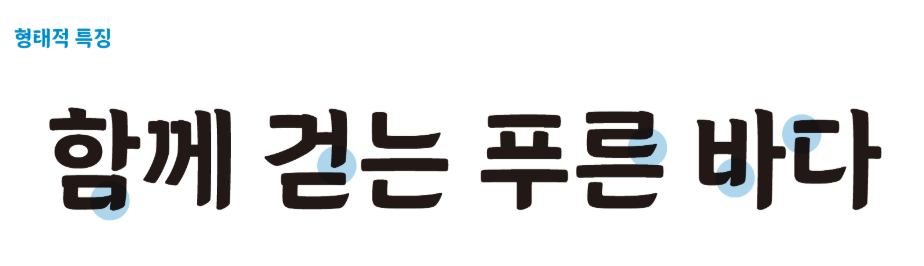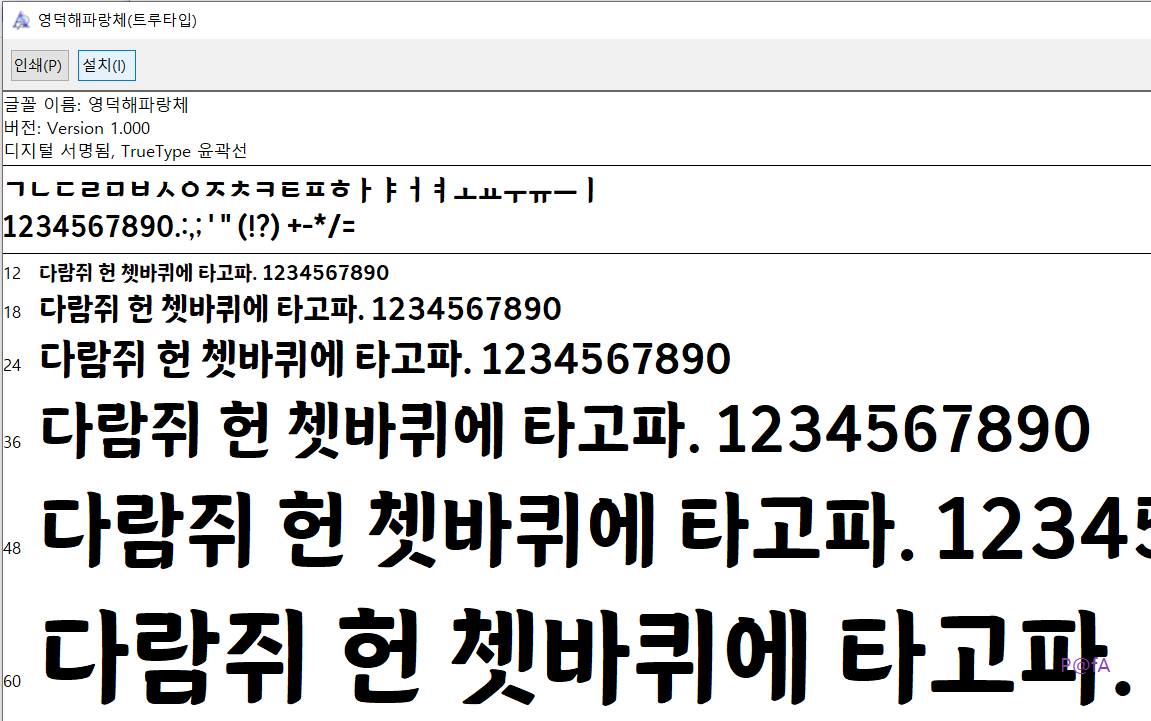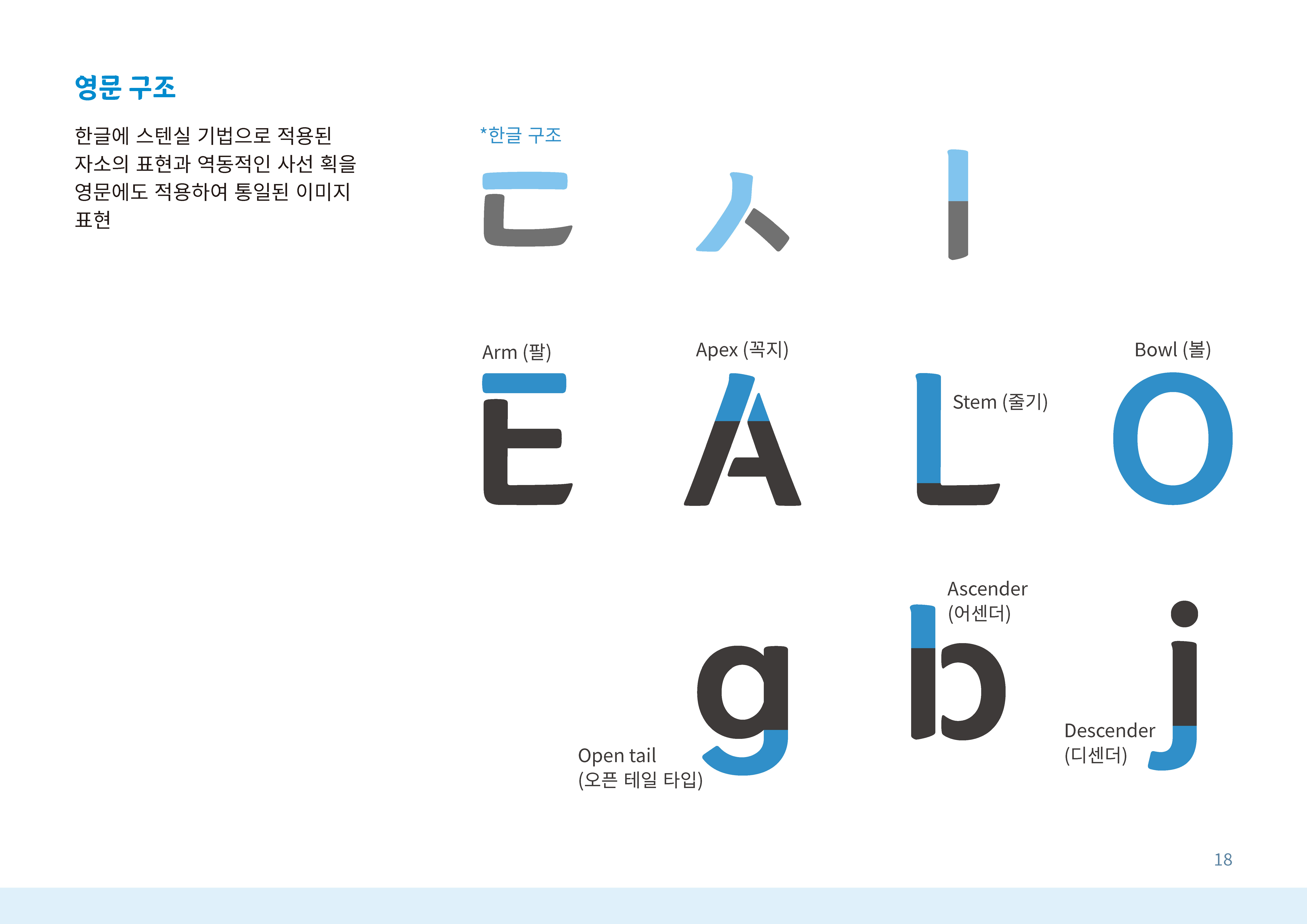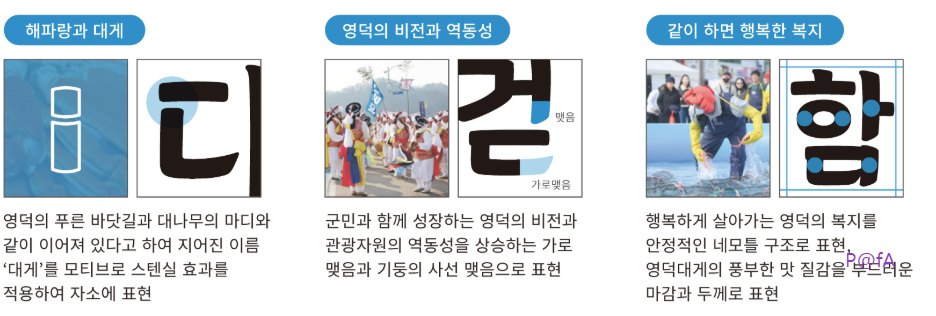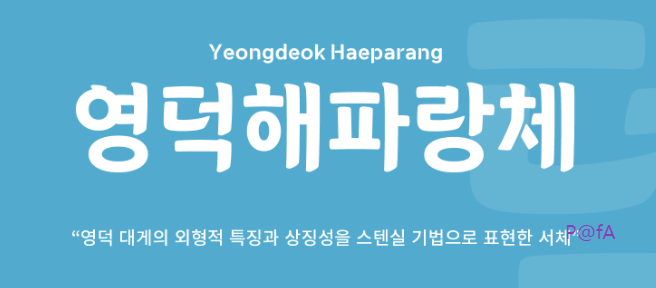
일부 자소에서 끊어진 듯 이어지는 효과가 나타나는 스텐실 폰트인 영덕 해파랑체를 다운로드하는 방법을 살펴본다. 더불어 누구나 무료로 사용 가능한 영덕 해파랑체를 컴퓨터에 설치하는 방법과 코딩 시에 활용하는 방법도 살펴본다.
스텐실 폰트 영덕 해파랑체 무료 다운로드
개인 및 기업 사용자에게 무료로 제공되는 즉, 누구나 개인적인 용도뿐만 아니라 상업적인 용도 즉, 영리 또는 비영리 목적으로도 무료로 사용할 수 있도록 제공하는 무료 폰트인 영덕 해파랑체를 소개한다. 영덕군은 자체 문서 및 책자, 안내판, 도시경관 등 실생활에 두루 사용할 수 있도록 무료로 제공하고 있다. 다음에서 영덕을 대표하는 대게의 외형적 특징과 상징성을 스텐실 기법으로 표현한 영덕 해파랑체를 무료로 다운로드해서 컴퓨터에 설치하는 방법을 비롯해서 사용하는 자세한 방법을 확인할 수 있다.
위의 이미지에서 보듯이 영덕 해파랑체는 일부 자소에 끊어진 듯 이어지는 스텐실 기법으로 구현하고 있는데, 여기에 사선 획과 가로 맺음으로 표현한 영덕의 역동성도 추가하고 있다. 이러한 역동성과 스텐실 기법 그리고 안정된 네모틀 구조는 영문에도 동일한 외형적 특징을 담아서 통일성을 주고 있다.
영덕 해파랑체는 한글 2780자에 라틴 95자 그리고 KS 약물 985자로 구성되어 있는 영덕군 전용서체 중 하나이다. 참고로 영덕군 전용서체는 해파랑체 이외에도 영덕바다체, 영덕대게체, 영덕블루로드체 등이 있는데, 모든 영덕전용서체는 무료로 사용이 가능하다.
더불어 아래에서 보듯이 해당 ttf 포맷의 글꼴 파일이 담긴 폴더에서 보기 옵션을 아주 큰 아이콘으로 설정하면 앞에서 언급했듯이 받침으로 사용된 자소 즉, ㄴ과 ㄹ에서 끝부분이 위로 향하는 역동성을 확인할 수 있다. 단, 해당 미리보기에서는 스텐실 기법은 확인할 수 없는데 즉, 모든 자소가 아니라 일부 자소에서만 스텐실 기법을 적용하고 있다.